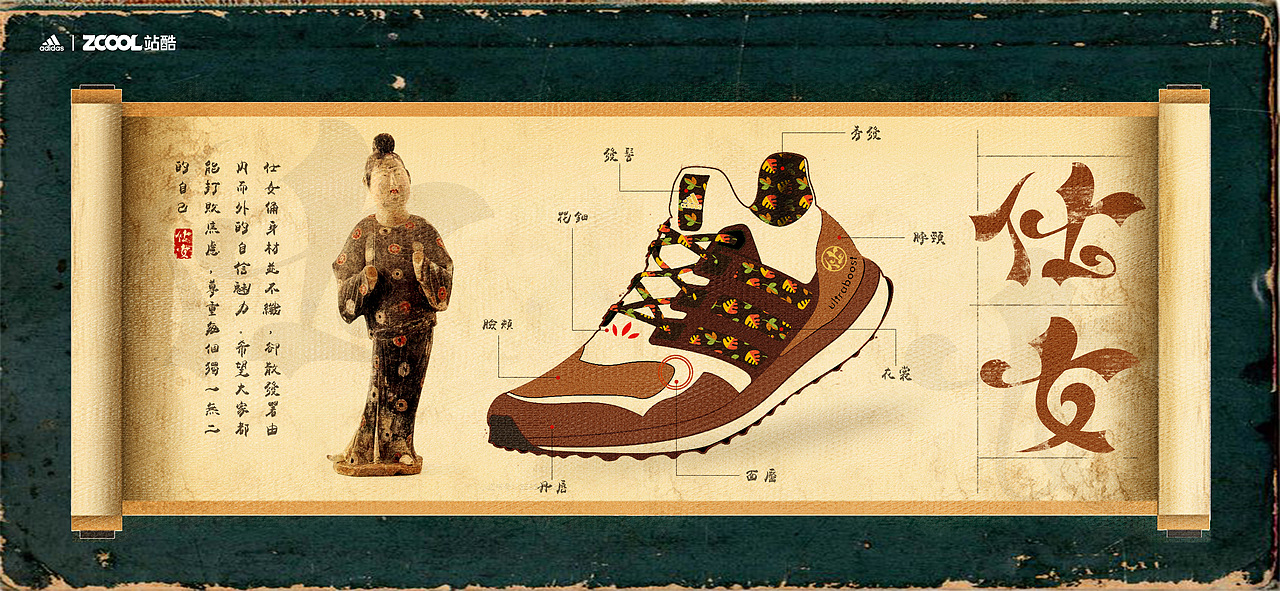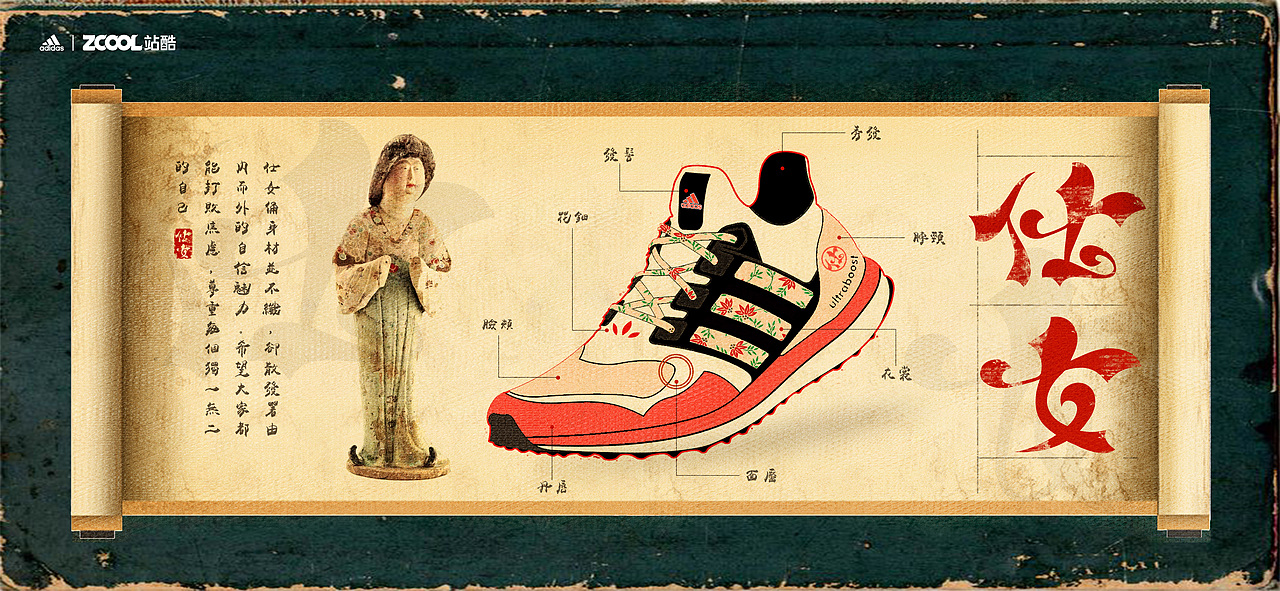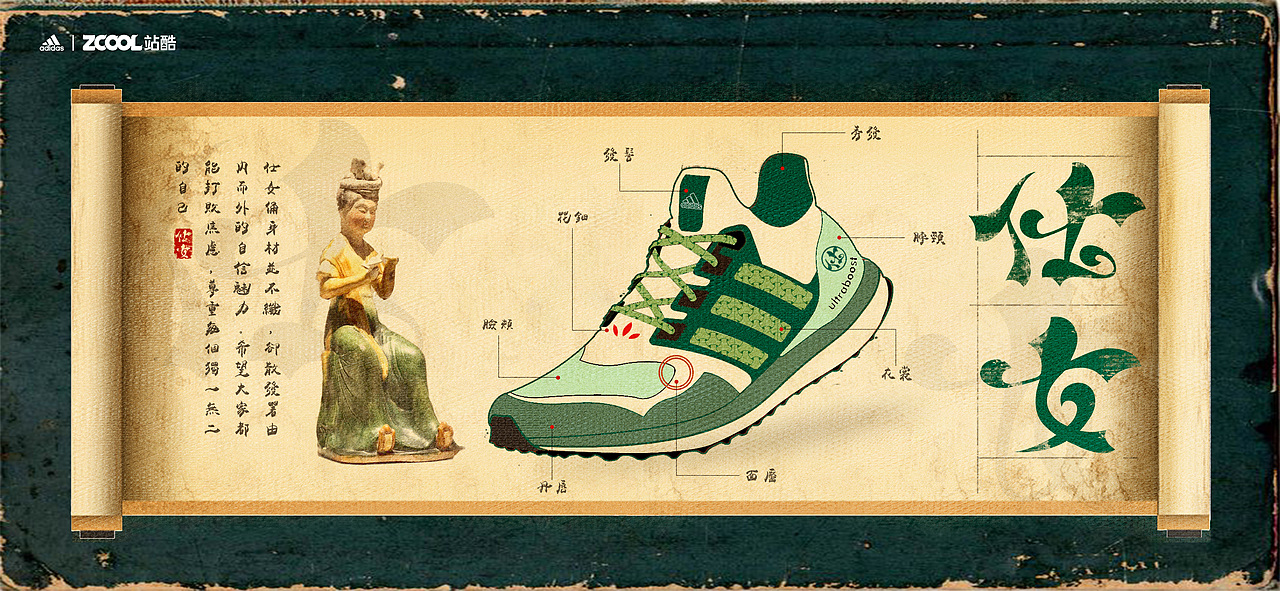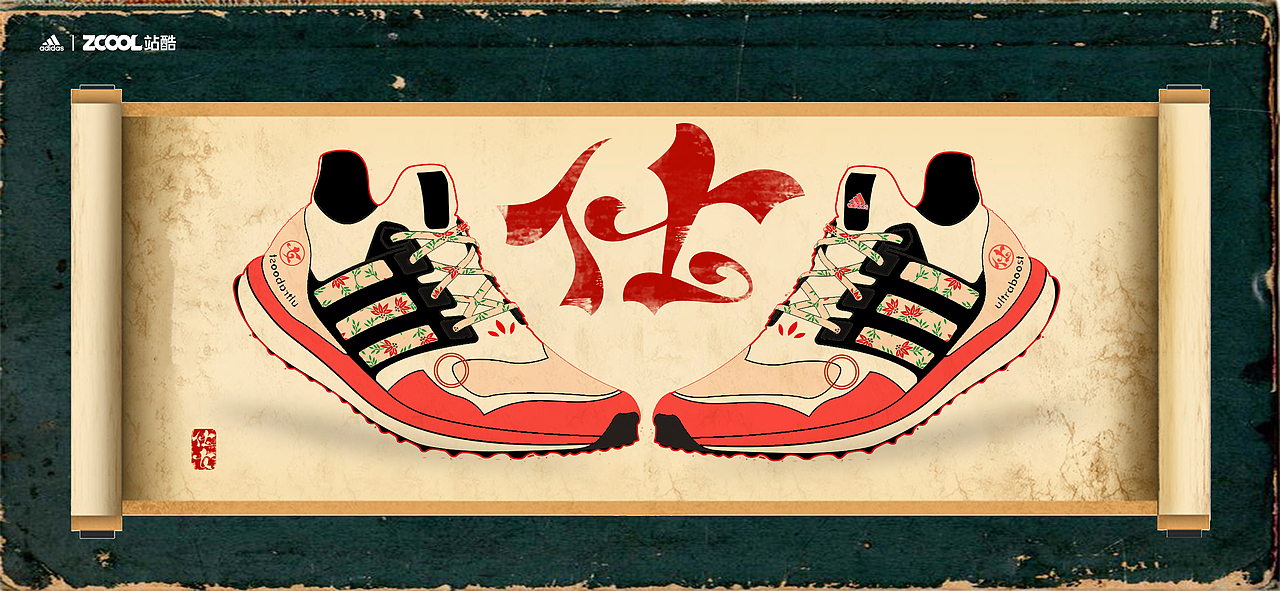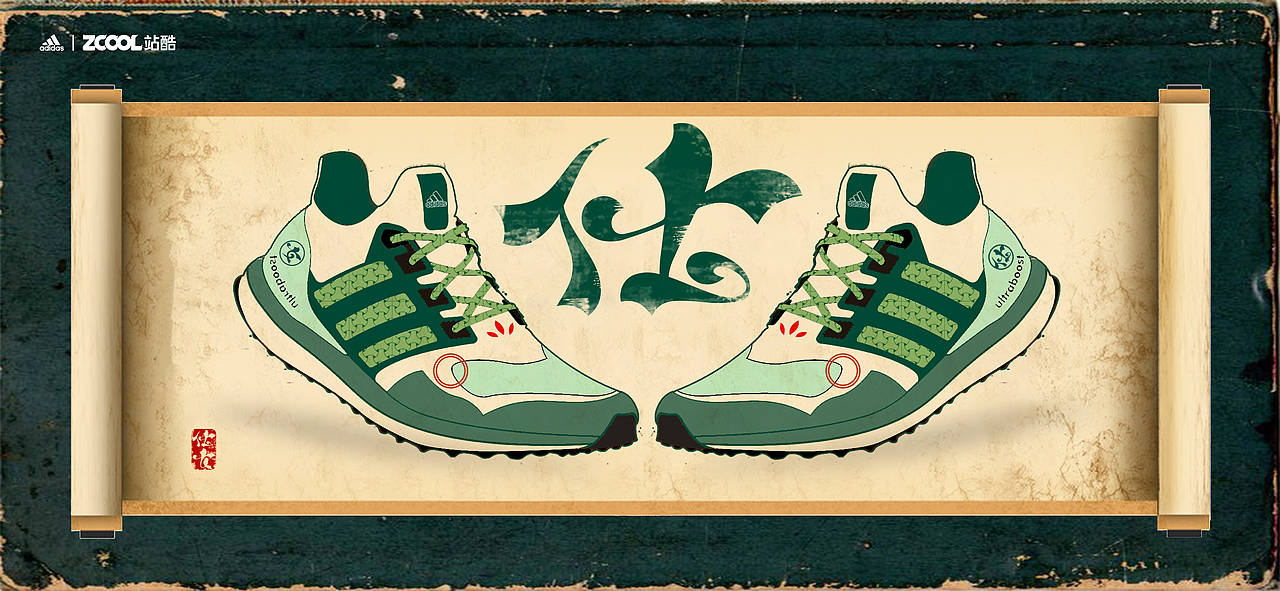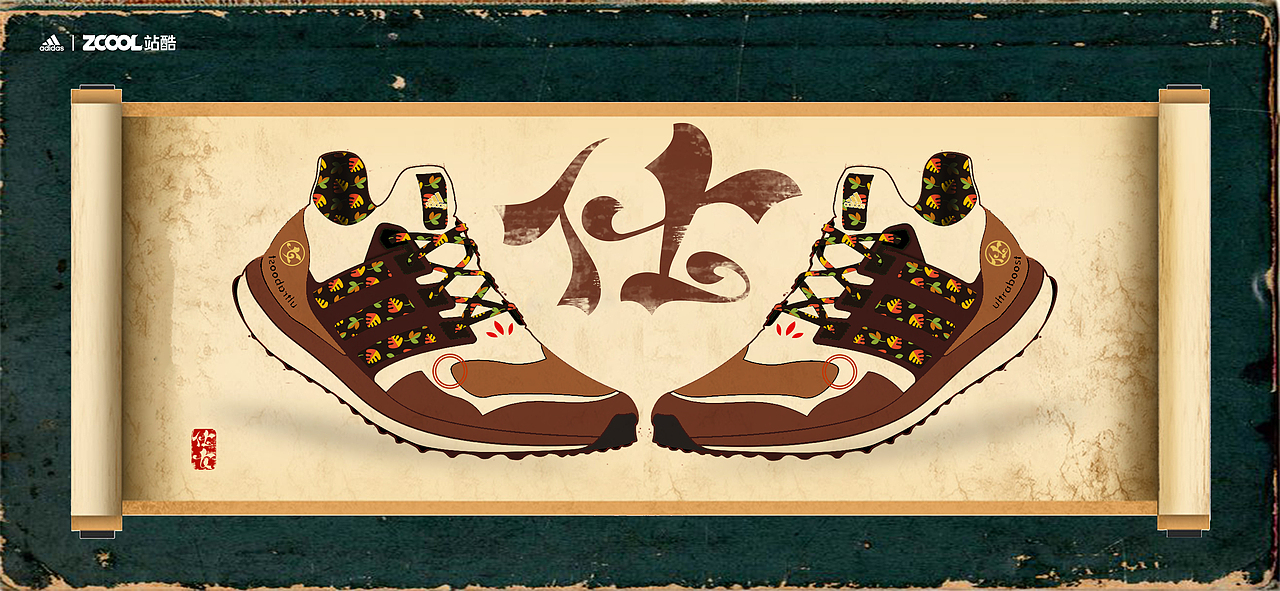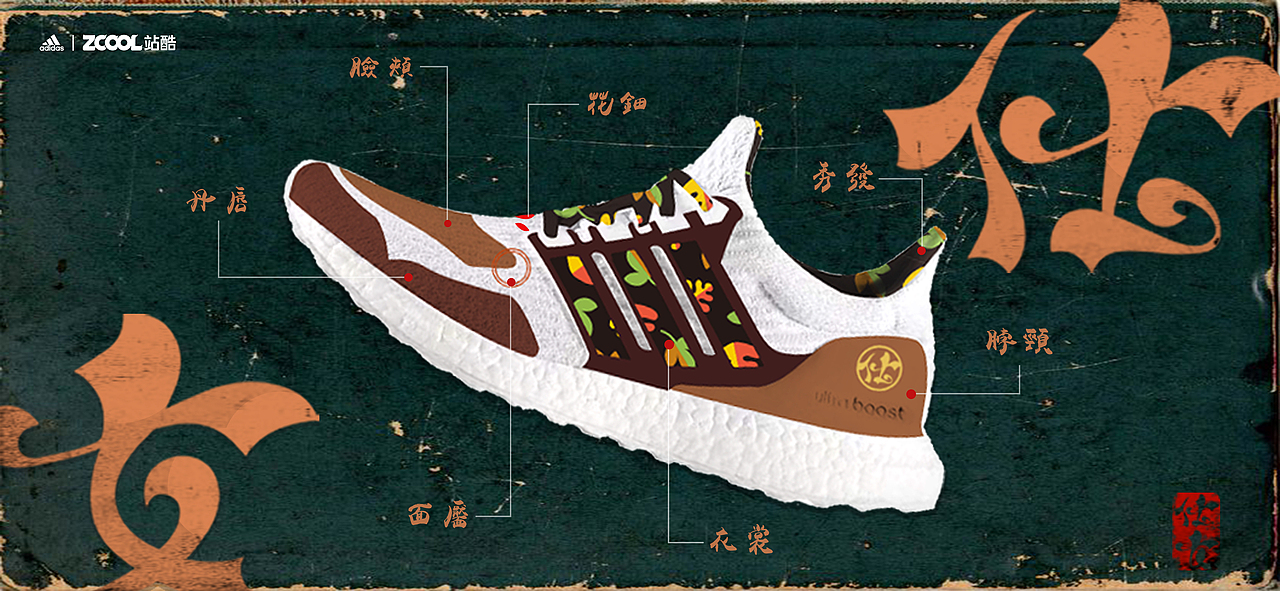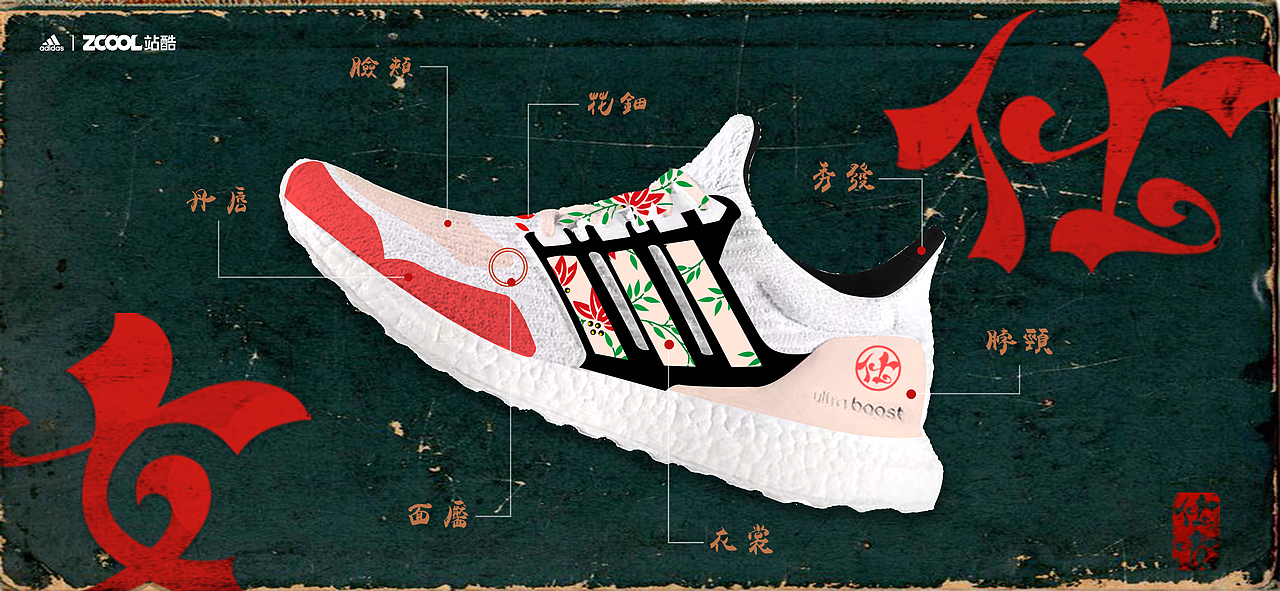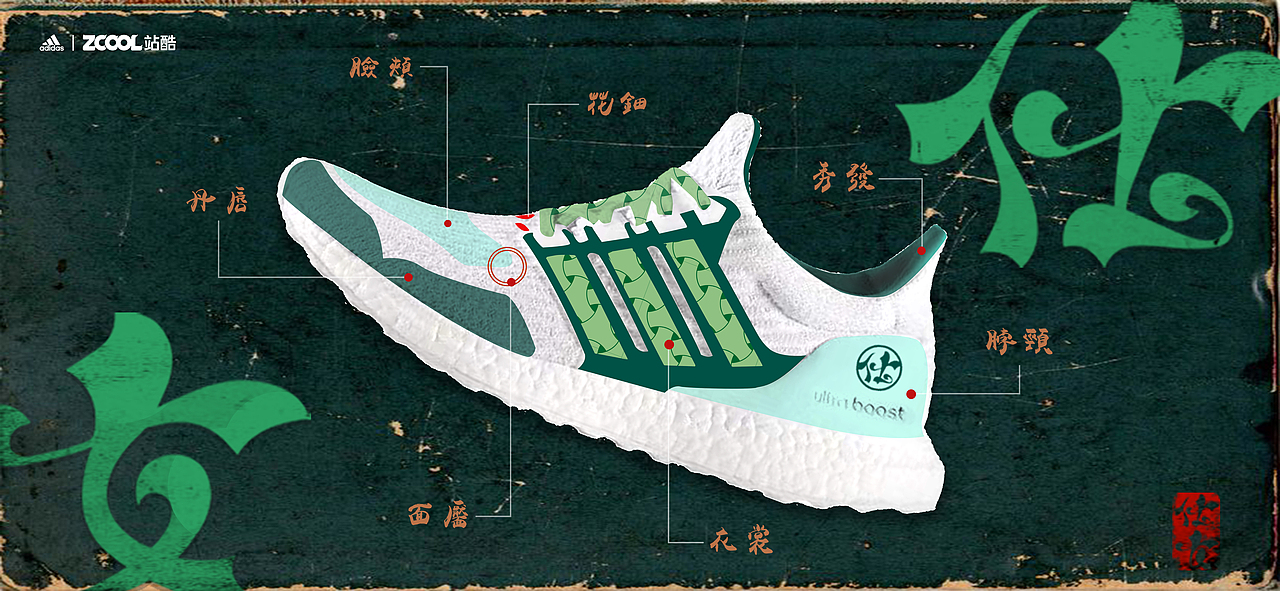
自在创作 “字”在奔跑——仕女
灵感来自于“唐代仕女俑”
仕女一词最早出现在《唐朝名画录》,仕女图画尽女儿家千姿百态,或活泼妍丽,或优雅沉静。丰肥雅容中的雅致,是盛唐仕女所独有的。这种繁荣、自信满足、大气的风貌是一个时代精神的写照。唐代仕女俑丰满的造型也可以说是以形写神,完美呈现了盛唐历史和文化的神韵和气质。
透过这些千姿百态的俑,我们得以一窥大唐美人的丰富日常。她们的身材并不纤细,却散发着由内而外的自信与优雅。在这个容貌焦虑肆意横行的现代社会,人们越来越消极或者说emo。我旨在希望人们可以摆脱容貌焦虑,大胆自信的进行社交以及运动。
希望每个穿上这款Ultraboost的人,都可以坦然地接受自己,积极地收集构成自信的元素,把自卑扔出天空外。
鞋子外观以仕女俑为原型,根据其特征进行了设计,包括极具象征性的仕女妆容细节如花钿,面靥,发髻都以一种喜闻乐见的形式体现在了鞋面上。